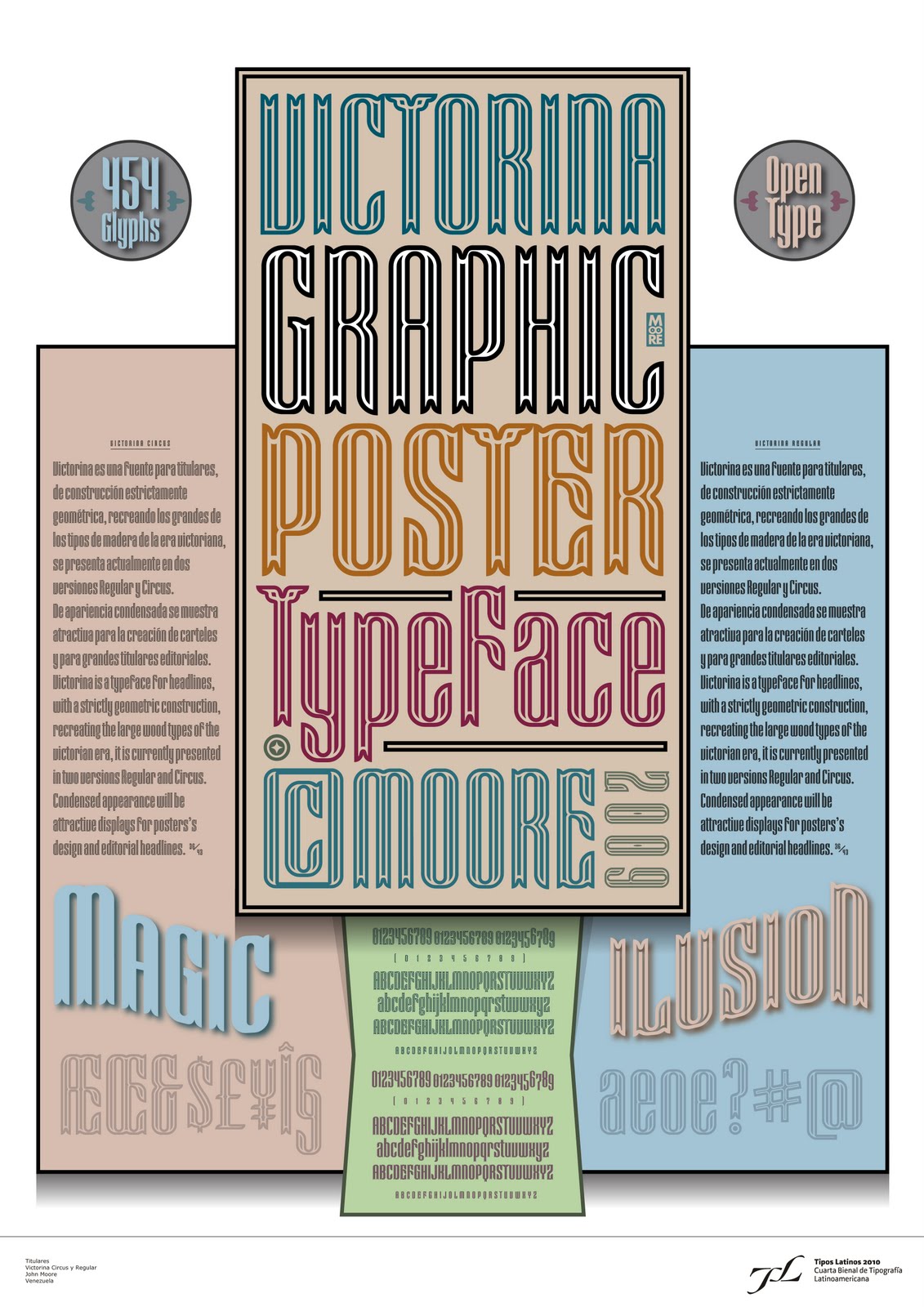
Inauguración 4ta Bienal de tipografía latinoamericana "
Tipos Latinos 2010" en Caracas - Venezuela
El 6 de mayo, se inauguró finalmente en Caracas la Cuarta Bienal de Tipografía Latinoamericana Tipos Latinos 2010 en la sede del Museo de la Estampa y del Diseño Carlos Cruz-Diez, con el extraordinario apoyo del Instituto de Diseño Darias y de la Fundación Museos Nacionales.
Con buen viento
Mucho ha cambiado el estado del desarrollo de la tipografía en nuestra región y en Venezuela desde que se inaugurara por vez primera en 2004 este magno evento dedicado a estimular la creación de fuentes tipográficas en Latinoamérica, mucho material inédito y de excelente factura ha fluido y ha sido mostrado en más de 10 países hermanos, gracias a la iniciativa y esfuerzo inicial-creo importante destacar- de Rubén Fontana. Venezolanos como John Moore, Johanny Franchi, Valter Cacurri, Carlos Fabián Camargo y Rodrigo Fuenzalida destacan ahora por su trabajo en el contexto tipográfico.
Hoy cuando arribamos a esta cuarta bienal, podemos argumentar con razones de sobra que la consolidación de la misma entre nosotros es etapa superada, lo cual ni remotamente implica que sea momento de descansar y disfrutar tempranamente de este logro colectivo, muy por el contrario, ahora nuestros mayores esfuerzos deben dirigirse a la creación de una plataforma cultural y educativa que cimiente definitivamente las virtudes y posibilidades reales y creativas de la tipografía a través de canales adecuados como la creación de cátedras de tipografía en las principales escuelas, institutos y universidades que forman diseñadores en nuestro país, así como también con la creación de menciones y especialidades en esta área como en la de diseño editorial, insistir en la apertura de talleres formativos libres que permitan un mayor acceso y participación a estudiantes y público interesado en general.
Es importante recordar la importancia que a este medio le confirieran personajes tan importantes como Francisco de Miranda, quién en su gesta precursora imprime - en la que será la primera imprenta en arribar a Venezuela- abordo del Bergantín Leander y navegando hacia nuestras costas, una maravillosa proclama independentista en la que se habla de libertad, en la que quedan grabadas para siempre con “tipos” la esperanza y la determinación que no nos abandonará nunca más de ser libres y que se consolidará en 1810 con un primer grito que terminó despertando y sacudiendo y a la América toda.
Juan Carlos Darias
Coordinador por Venezuela
Tipos Latinos.
El Ministerio del Poder Popular para la Cultura a través de la Fundación Museos Nacionales y el Instituto de Diseño Darias invitarón a la apertura de la muestra, Tipos Latinos 2010. Cuarta Bienal de Tipografía Latinoamericana. Considerada como el mayor evento que celebra el diseño tipográfico de América Latina.
Una vez más en el Museo de la Estampa y del Diseño Carlos se presentanon los proyectos seleccionados de este evento. Tipos Latinos ha alcanzado en cada nueva convocatoria mayor proyección por la calidad e innovación de las propuestas presentadas, así como por la incorporación de más países; es ya una referencia internacional siendo un espacio en el que se reconoce, confronta y se divulga el talento latinoamericano por la creación y experimentación de tipografías que aspiran modelar una identidad tipográfica propia. Sus organizadores han expresado “la Bienal es un estímulo a la creciente producción tipográfica latinoamericana y un impulso a la reflexión sobre la actualidad y el futuro de esta disciplina”.
“Generalmente, cuando hablamos de tipografía, nos referimos a fuentes extranjeras que no se adaptan a nuestras realidades o costumbres; por eso, esta Bienal nos permite reafirmar la cultura latinoamericana, generando obras gráficas que surgen de nuestro contexto, lo cual mejora la calidad de nuestros comunicadores visuales”. (Rubén Fontana - Maestro del diseño gráfico argentino, creador de la Bienal).
La muestra reúnió proyectos de creación individual y colectiva, tanto de importantes diseñadores que continúan su labor en esta área, así como de nuevos profesionales del área y estudiantes que demuestran su gran capacidad creativa y su compromiso con el diseño.
Se exhibierón un total de setenta y ocho (78) proyectos, siete (7) de ellos considerados de excelencia; distribuidos según las siguientes categorías en: doce (12) proyectos de fuentes para Texto, veintiséis (26) fuentes para Título, cuatro (4) fuentes para Pantalla, diez (10) fuentes Experimentales, cuatro (4) fuentes para Misceláneas, catorce (14) fuentes de Familia y ocho (8) proyectos de Diseño con fuentes latinoamericanas.
Las categorías presentadas se referían a Diseño de fuentes latinoamericanas para Texto (fuentes destinadas a la composición de textos), Título (fuentes orientadas a la composición de textos breves en cuerpos grandes), Pantalla (fuentes diseñadas para el uso exclusivamente digital), Experimental (fuentes en donde no prevalece la lectura), Misceláneas (fuentes iconográficas), Familia (sistema de fuentes compuestas por dos o más variables), y Diseño con fuentes latinoamericanas correspondientes a proyectos realizados con fuentes diseñadas por tipógrafos latinoamericanos.
La selección se realizó en la ciudad de Montevideo, Uruguay, del 22 al 23 de marzo de 2010 en la Universidad ORT. El jurado calificador estuvo conformado por Marcelo Romero (Argentina), Fabio López (Brasil), Hugo Rivera Scott (Chile), César Puertas (Colombia), Paco Calles (México), Juan Heilborn (Paraguay) y José de los Santos (Uruguay), todos destacados representantes del diseño en Latinoamérica quienes evaluaron cuatrocientas cuarenta y ocho (448) propuestas.
Tipos Latinos 2010, cuenta ya con doce países sedes, Argentina, Bolivia, Brasil, Chile, Colombia, Ecuador, Guatemala, México, Perú, Paraguay, Uruguay y Venezuela; progresívamente en cada uno de ellos, se realizará esta exhibición.
Unas palabras de la diseñadora Mercedes Gardner acompañada para esta ocasión por Juan Carlos Darias abrieron oficialmente esta interesante muestra. Que nos permite acercarnos al desarrollo creativo de dingbats por parte de nuestros colegas y hermanos brasileños.